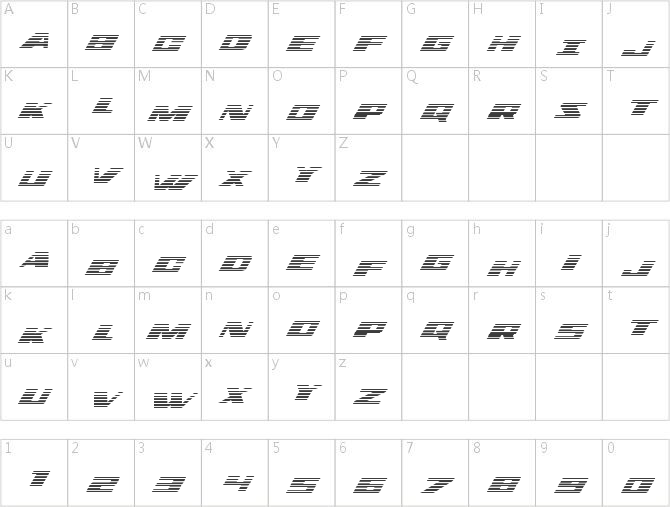
dassaultgradital 詳情頁(yè)
dassaultgradital字體字庫(kù)是一款讓人賞心悅目、百看不厭的英文字體,適合各類廣告和產(chǎn)品包裝設(shè)計(jì)應(yīng)用,字體大小0.05MB,格式為ttf字體,上傳用戶是誠(chéng)澤永信,作者/版權(quán)方為未知